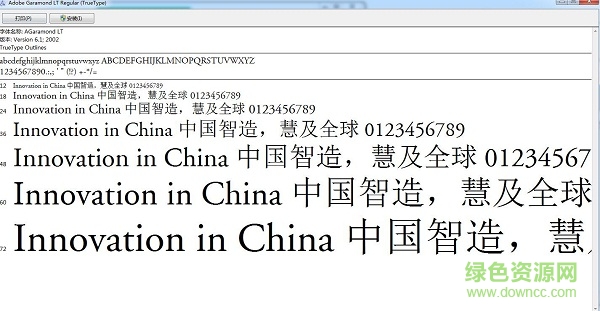
agaramondlt-bold和agaramondlt regular两款衬线字体是绿色资源网为需要的朋友整体的免费合集包,这套字体流畅干净,起笔和收笔十分分明,稳定实用,欢迎大家下载体验!
按造型类分类的话,基本可以分为6大类别:Serif、Sanserif、Blackletter、 Egyptienne、Script、Mono。其中Serif和Sanserif是2个最大的类别,绝大多数的常用字 体都是出自其中。